不管是平面设计师还是UI设计师,在工作中几乎都会用到字体。如今形形色色的字体日增月盛,也就有了不同的性格和气质。选择使用一款字体的时候,除了考虑它的易读性,更多考虑的是这款字体能否准确地传达出对产品独有的气质。
那么应该怎么选择合适的字体呢?
或许这篇文章能够为你提供一些思路。
第一节:选择更符合主题气氛的字体字形
案例1–战争气质
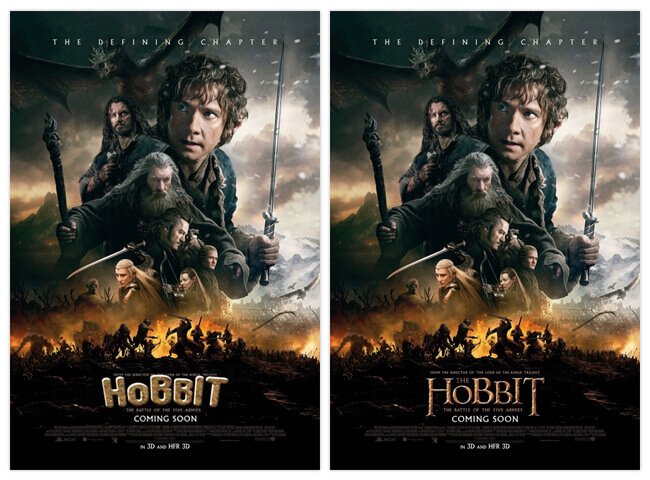
原型/圆体、哥特体
左图字体所传达的气质:趣味、活泼;
显得对这部战争类型的电影所表现的气质格格不入。
右图字体所传达的气质:哥特、凌厉;
采用了具有装饰性的衬线字体,衬线字体的特点在于线条交接处和末端具有明显的粗细变化和装饰,使字体气氛感觉犀利,加上纹理质感处理,便有了神话意境和哥特式惊悚的味道,很好的衬托出电影本身的气质。
案例2—文艺气质
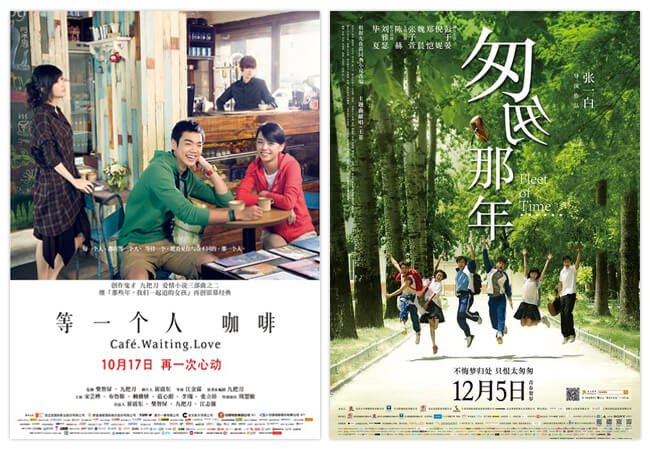
原型/宋体
上面两张电影海报应用的字体都是宋体,宋体的衍生有很多,又长有扁,有胖有瘦。一般用于书籍印刷。而在电影界上这类型字体多用于文艺片,正如案例中,两部都是文艺温馨的爱情片,运用宋体进行排版处理,既显得清新又文艺。
案例3—女性气质
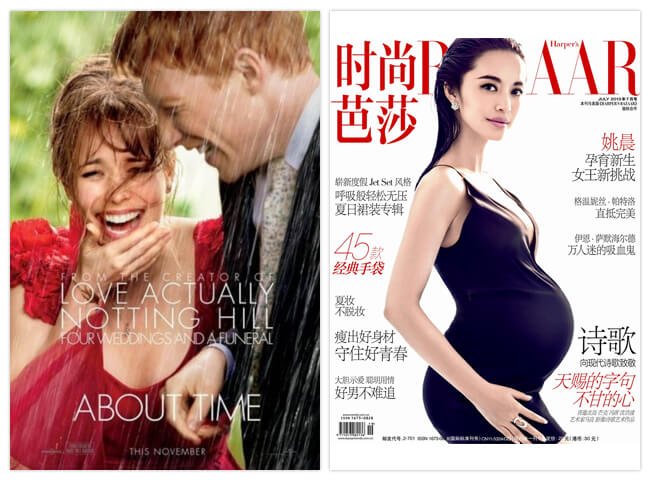
原型/细线体、衬线体
字如其人,女性的特点是细致优雅、苗条细长;常被用作化妆品、女性杂志、艺术等女性主题领域。
案例4—男性气质
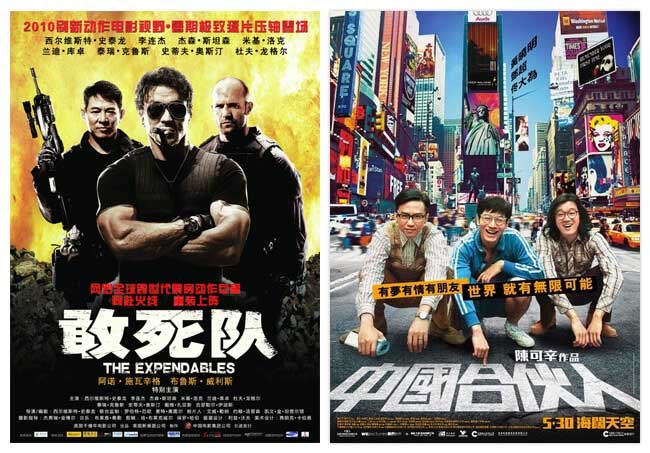
原型/黑体
作为强现代感的无衬线字体—黑体,给人感觉粗壮紧凑,颇有力量感,可塑性很强,对比案例3的细线体,即可表现为阳刚有力的男性气质,也可以变成纤细优雅的女性气质。
案例5—历史文化气质
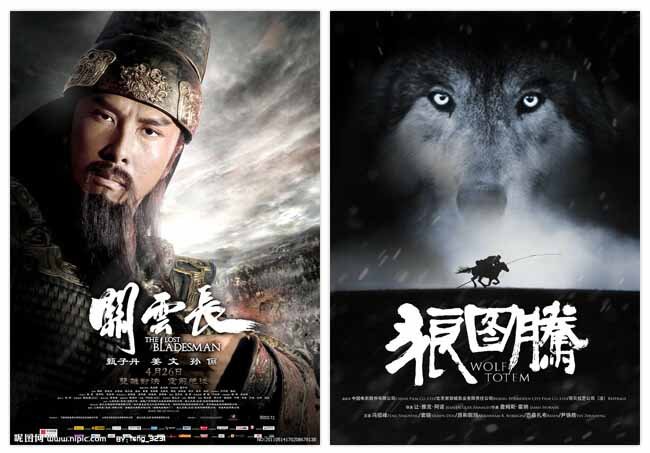
原型/书法字体
书法字体具有很强的设计感与艺术表现力,运用好的话往往是点睛之笔。各式各样的书法字体有着自己独特的细腻的特点,把握好这一点,既能给电影增加文化内涵,也能衬托出电影的气质。
第二节:字体艺术化设计
案例1—游戏角色
原型/菲奥娜、凯南 作者/叶小凉
相信玩过LOL的人对这两个角色名字都深有感触,作者把角色本身的性格和气质通过字体表现得淋漓尽致;例如菲奥娜是一位心狠手辣的女剑士,挥舞起剑下手快准狠;作者在字形设计上呈现出了角色本身的特质,加上被剑砍下的视觉效果,很好的体现出了菲奥娜所散发的独特气质。
案例2—移形换影
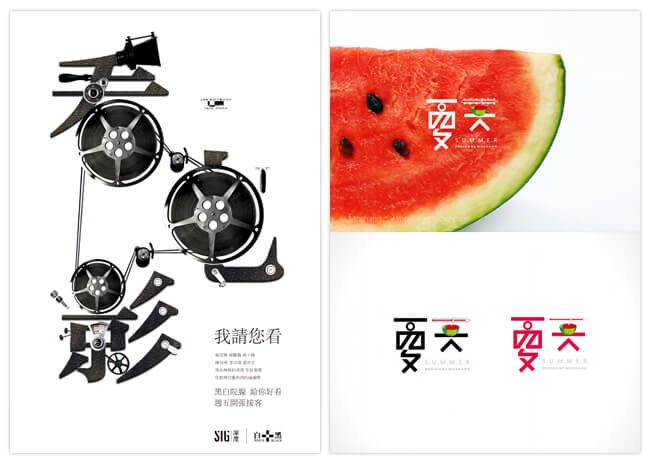
原型/生活 左图作者:未知/右图作者:陌Moshang
这是一款很有趣味的字体作品,通过字意本身所表达的情感,巧妙的把图形跟字体结合起来。比如“看电影”融入了真实的胶卷电影转轴;“早安”融入了太阳和早餐,夏天让人联想到西瓜,带给人冰凉夏日的感觉;
第三节:生活中常见字体运用
前面给大家讲了字体的气质,接下来给大家挑选的几组日常生活常见的品牌类型,分别是报刊、运动服饰、奢侈品、手机;试着去感受一下他们所散发的气质是怎么样的呢?
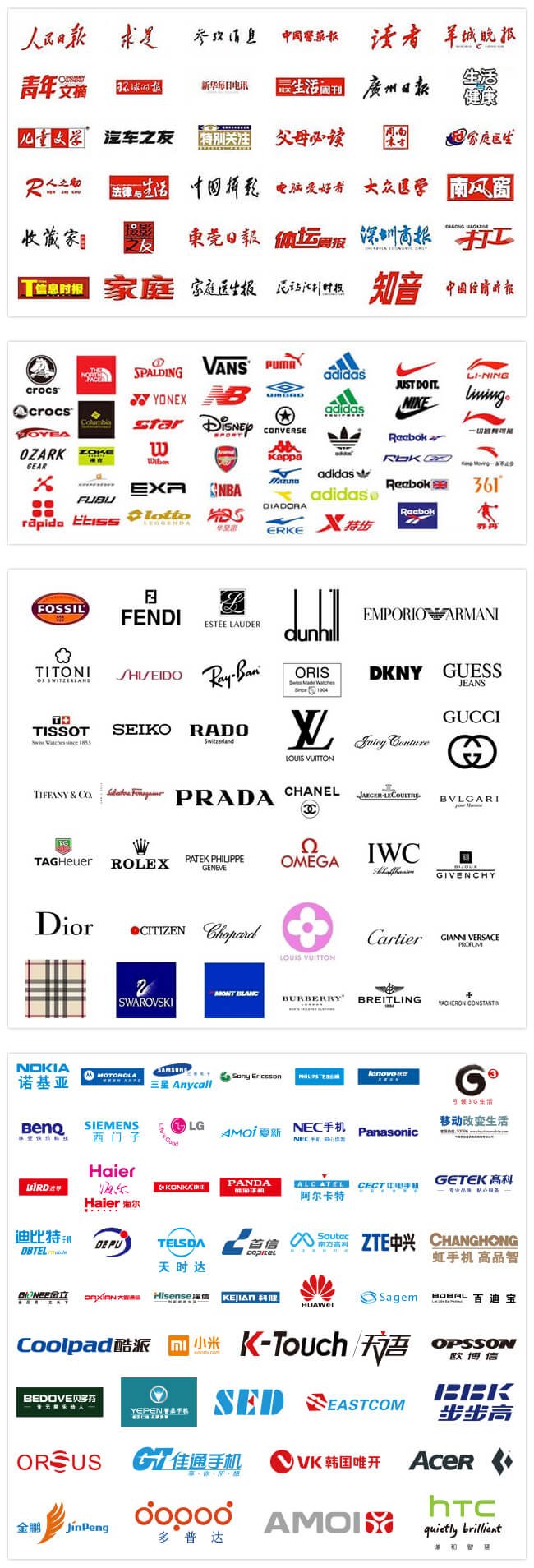
小结:
不管是中文还是英文,文字不仅是传达信息的载体,也是设计中的重要元素,设计过程中尽量保证文字的阅读性,在严谨中寻求突破。经过艺术设计的字体,可以使信息更形象、更美感的铭记于你心中。对于字体这门科,还需要我们不断的去探究和学习。本文主要是对字体设计的一些粗浅的感受,欢迎大家一起交流与探究。